Comment voulez-vous que je n’ai pas de sympathie pour Marion Bataille qui déclare ceci…«Le rituel de création est toujours le même. “Lorsqu’un éditeur fait appel à moi, je lis d’abord le texte et puis je laisse passer un peu de temps, pour m’imprégner de l’histoire et qu’une image s’impose à mon esprit» (SVMac… passeuse d’émotions). Il faut suivre ce lien pour apprendre plus sur la vie et l’œuvre de l’artiste née en 1963 et ayant un parcours exemplaire de formation aux arts graphiques.
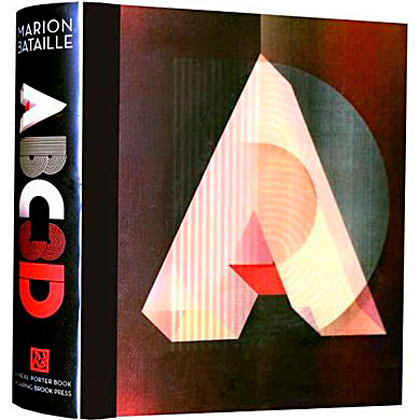
Un interview de Marion Bataille ici .